Saat ini, desain kontemporer menjadi salah satu tren yang sangat populer di dunia desain grafis. Desain ini mengusung konsep minimalis, bersih, dan modern yang memberikan kesan segar dan up-to-date. Salah satu elemen penting dalam desain kontemporer adalah pemilihan font yang tepat. Font modern terbaik yang digunakan harus mampu memperkuat pesan yang ingin disampaikan dan menciptakan tampilan yang menarik.
Apa sebenarnya yang dimaksud dengan font modern? Secara umum, font modern merujuk pada jenis huruf yang telah digunakan dalam dunia desain kontemporer sejak abad ke-18. Dengan garis dan bentuk geometris yang menjadi ciri khasnya, gaya font ini ditampilkan dengan tampilan yang bersih, jelas, dan mudah dibaca.
Meskipun tetap mengikuti perkembangan zaman, font modern tetap mempertahankan sifat kesederhanaan atau minimalis. Sangat jarang, bahkan hampir tidak ada, font modern yang terkesan berlebihan atau terlalu mewah. Inilah sebabnya mengapa gaya font ini tetap relevan untuk berbagai jenis desain.
50 Font Modern Terbaik untuk Desain Kontemporer
Dalam kategori font modern, terdapat banyak pilihan font unik dan estetis. Jenis font ini dapat Anda sesuaikan dengan kebutuhan desain mulai dari pembuatan lamaran pekerjaan, kartu ucapan, hingga desain latar belakang untuk kutipan yang ingin Anda bagikan di media sosial.
Tidak peduli apa keperluan desain Anda, pastikan untuk memilih gaya font yang paling sesuai agar mencapai tujuan secara efektif. Di bawah ini, kami telah mengumpulkan beberapa font modern terbaik yang cocok untuk desain kontemporer:
01 Lombok
Lombok – Tipografi Serif yang Unik dari Alexandre Pietre
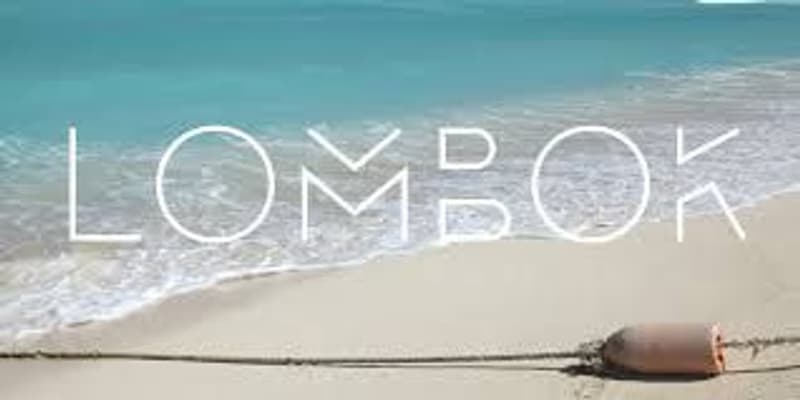
Font modern pertama adalah Lombok, karya Alexandre Pietre. Dengan asal-usul dari tipografi serif, font ini menampilkan huruf tanpa garis proyeksi atau ikal di ujungnya. Meskipun tampak samar, gaya font ini tetap tegas dan jelas terlihat.
02 Ailerons
Ailerons – Inspirasi Pesawat Terbang 1940an oleh Adilson Gonzales de Oliveira Junior
Adilson Gonzales de Oliveira Junior menciptakan Ailerons, sebuah font unik yang terinspirasi oleh model pesawat terbang pada era 1940an. Ujung setiap hurufnya miring dan sedikit melengkung dengan detail yang halus.
03 One Day
One Day – Font Ramping dengan Sentuhan Visual Menarik dari Nawras Moneer
One Day, karya Nawras Moneer, adalah font ramping dengan huruf besar yang memikat. Bentuk font bulat dan garis putus-putusnya menambahkan daya tarik visual pada judul utama.
04 Cooper Hewitt
Cooper Hewitt – Sans Serif Kontemporer dari Museum Desain Cooper Hewitt Smithsonian
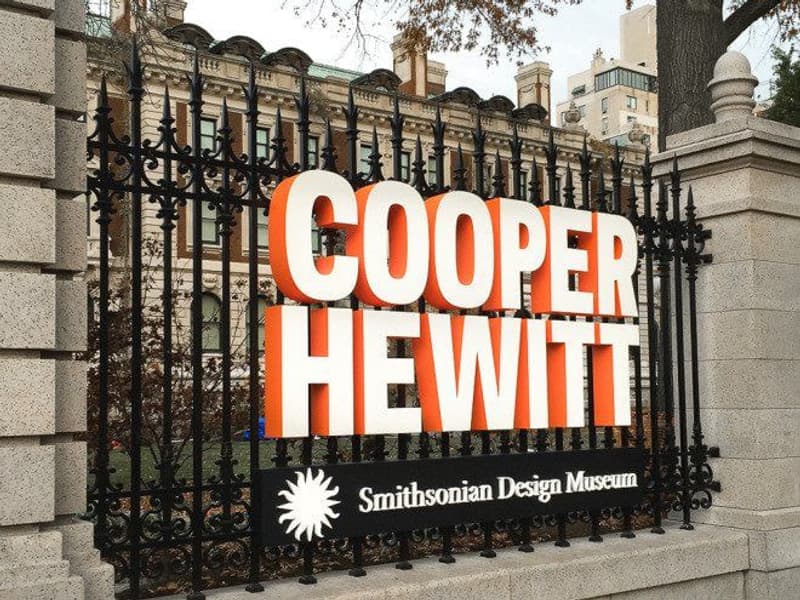
Museum Desain Cooper Hewitt Smithsonian melibatkan perancang Chester Jenkins untuk menciptakan font sans serif kontemporer sebagai bagian dari revitalisasi bangunan dan identitasnya. Font ini tersedia gratis untuk keperluan umum dan cocok digunakan dalam desain brand masa kini.
05 Aqua
Aqua – Garis Lurus Kontras dengan Bentuk Bulat dari Laura Pol
Font unik Laura Pol, Aqua, menampilkan garis lurus kontras dengan bentuk yang sangat bulat. Huruf besar didominasi oleh sudut yang kuat, sementara huruf kecil memiliki lingkaran halus yang mendominasi.
06 Kolikö
Kolikö – Sans Serif Geometris dengan Karakter Latin dan Cyrillic dari Fontfirma
Keluarga font Kolikö dari Fontfirma memiliki karakter Latin dan Cyrillic dalam gaya reguler, tipis, dan tebal. Sebagai font sans serif geometris, Kolikö memiliki struktur bersih yang cocok untuk berita utama yang tebal.
07 Polya
Polya – Modern dengan Inspirasi Jaring Poli-Poli oleh Pilar Adrien
Pilar Adrien menciptakan font Polya yang terinspirasi dari jaring poli-poli, yakni jala untuk pemodelan komputer 3D. Font ini memiliki bentuk tebal dan tampilan yang ringan, menampilkan gaya multi-fungsi.
08 Radnika
Radnika – ‘Medium’ yang Menjembatani Kesenjangan Tipografi oleh Alfredo Marco Pradil
Alfredo Marco Pradil mendeskripsikan font Radnika-nya sebagai “tipe pekerja keras.” Ini adalah jenis huruf multi-fungsi yang menjembatani kesenjangan antara tipografi abad ke-19 yang kuat dan ekspresif, dan tipografi abad ke-20 yang halus dan buram.
09 Modeka
Modeka – Ringan dan Elegan dengan Detail yang Membulat dari Gatis Vilaks
Modeka, hasil karya Gatis Vilaks, adalah font ringan dan elegan yang menggabungkan sudut dengan detail yang membulat. Set karakternya menampilkan persimpangan yang terlihat antara bagian masing-masing elemen.
10 Higher
Higher – Ideal untuk Berita Utama dengan Tampilan Memanjang dari Marisa Passos
Awalnya dirancang untuk proyek sekolah, font Higher oleh Marisa Passos kemudian ditawarkan secara gratis untuk penggunaan umum. Ideal untuk berita utama, Higher memiliki tampilan yang memanjang dengan bentuk yang rapat pada bagian atas atau bawah setiap karakter.
Unduh di Bēhance.
Baca juga: 12 Font Ramadhan Khusus Desain Bertemakan Lebaran
11 Nordik
Nordik – Eksperimental dan Terinspirasi oleh Runic Norwegia dari Yana Bereziner
Nordik adalah font modern bergaya eksperimental yang didesain oleh Yana Bereziner. Terinspirasi oleh runic Norwegia, font ini mengadopsi huruf yang digunakan sebagai bahasa Jerman sebelum diadaptasi menjadi alfabet Latin.
Unduh di Bēhance.
12 Komoda
Komoda – Font Ramping dengan Gaya Modern dari Asia Ang
Asia Ang menciptakan Komoda, sebuah font ramping yang sangat cocok untuk jenis huruf berita utama dan judul. Desainnya terlihat sangat modern dengan bingkai garis persegi panjang yang mengelilinginya.
Unduh di Bēhance.
13 Kollektif
Kollektif – Alternatif Kontras Rendah dari Brave New Fonts
Sebagai alternatif untuk tipografi berkontras rendah pada abad ke-21, Brave New Fonts merancang Kollektif. Font aesthetic ini dapat digunakan untuk tampilan dan blok teks, tersedia dalam dua gaya serta dua bobot.
14 Achi
Achi – Font Eksperimental dengan Sentuhan Art Deco dari Shibu PG
Achi, karya Shibu PG, adalah font eksperimental dengan gaya modern dan kontemporer. Garis ganda stem dan stroke menambahkan sentuhan detail Art Deco yang memukau.
Unduh di Bēhance.
15 Parley
Parley – Gaya Modern dengan Garis Diagonal Menarik dari Filipe Rolim
Filipe Rolim menciptakan Parley dengan garis diagonal yang menarik, memotong setiap huruf dan angka. Beberapa potongan menjadi bagian dari karakter, sementara yang lain menambahkan detail tambahan yang unik.
Unduh di Bēhance.
16 Aroma
Aroma – Gaya Kontemporer dengan Sentuhan Retro dan Kaligrafi dari Laura Pol
Laura Pol kembali menciptakan font, Aroma, yang tersedia dalam versi huruf tebal dan tipis. Bergaya kontemporer dengan lengkungan dan terminal siku yang sedikit retro dan kaligrafi.
Unduh di Bēhance.
17 Boxing
Boxing – Font Kuat Terinspirasi Poster Tinju Retro dari Tano Veron
Tano Veron memberikan pukulan berat dengan font Boxing yang memiliki bentuk kuat, memanjang, dan rapat. Terinspirasi oleh poster tinju retro, font ini sesuai dengan namanya yang kuat.
Unduh di Bēhance.
18 Minimalust
Minimalust – Font Bersih dan Minim dengan Sentuhan Vintage dari Pratama Yudha
Minimalust, desain Pratama Yudha, adalah font bersih dan minim yang terinspirasi dari tulisan tangan dan cetak vintage. Jenis huruf sans serif ini memiliki tepi yang halus dan sudut yang membulat.
Unduh di Bēhance.
19 Hyped
Hyped – Geometris dan Modern dengan Inspirasi Art Deco dari Med Ness
Med Ness membawa font Hyped dengan bentuk geometris dan ruang negatif. Beberapa karakter terinspirasi oleh Art Deco, sementara yang lain memiliki sentuhan postmodernis Memphis.
Unduh di Bēhance.
20 Metria
Metria – Geometris Serbaguna dengan Sentuhan Organik dari Jake Lunde
Metria adalah jenis huruf geometris serbaguna dengan sudut konsisten dan lingkaran yang tidak sempurna. Menurut desainer Jake Lunde, font ini terinspirasi dari bentuk geometris yang kaku yang diinfus dengan kurva organik untuk membuat kata-kata menjadi hidup.
Unduh di Bēhance.
21 Arenq
Arenq – Retro dan Futuristik dari Paulo R
Paulo R memberikan font gratis bernama Arenq, dengan bentuk dua garis yang memancarkan daya tarik retro dan futuristik. Font ini tampil sangat efektif dengan gradien atau pudar pada setiap karakter.
Unduh di Dafont.
22 Fontaine
Fontaine – Inspirasi Art Deco untuk Tampilan Dramatis dari Freebies PSD
Fontaine, mengambil inspirasi dari gaya Art Deco, cerita detektif, serta berita utama dan iklan vintage, terlihat sangat cocok untuk judul poster film. Font ini jelas, mudah dibaca, dan memberikan nuansa drama yang tepat.
Unduh di Freebies PSD.
23 Brassie
Brassie – Modern dan Kontemporer Serif dari Ryan Welch
Brassie, ciptaan Ryan Welch, merupakan font serif pertama dalam daftar ini. Meskipun memiliki serif kecil, ini tidak mengurangi pesonanya karena tetap menjadi font yang benar-benar modern dan kontemporer.
Unduh di Bēhance.
24 Moka
Moka – Tampilan Modern untuk Logo Kopi dari Liz Withers
Liz Withers menciptakan Moka sebagai jenis tampilan modern untuk logo kopi. Meskipun tidak dipilih oleh kliennya, Liz memutuskan untuk membagikannya secara gratis di Bēhance. Font sans serif ini memiliki ukuran besar pada garis dan outlinenya, memberikan sentuhan tulisan tangan yang unik.
Unduh di Bēhance.
25 Perfograma
Perfograma – Inspirasi dari IBM Harvard Mark 1 dari Fontfabric
Perfograma terinspirasi oleh IBM Harvard Mark 1, komputer elektro-mekanis yang membaca instruksi dari pita kertas 24 saluran punched paper tape. Meskipun konsepnya berasal dari tahun 1937, font ini tetap dianggap modern.
Unduh di Bēhance.
26 Ministry
Ministry – Elegan dan Memanjang dari Victor Tognollo
Ministry, hasil karya Victor Tongollo, adalah jenis huruf sans serif yang elegan dengan bentuk memanjang, kurva halus, dan batang serta ekor yang menarik, dilengkapi dengan elemen khas lainnya.
27 Unik2
Unik2 – Kontemporer dengan Sentuhan Retro dan Futuristik dari Fonts of Chaos
Unik2 dari Fonts of Chaos menampilkan tampilan kontemporer sambil masih memancarkan nuansa retro dan futuristik. Meskipun tanpa bentuk lingkaran, sudut dan terminalnya dibulatkan untuk memberikan kesan yang halus secara keseluruhan.
28 Nagasaki
Nagasaki – Terinspirasi oleh Poster Klasik dari Sasha Lacob
Font Nagasaki karya Sasha Lacob terinspirasi oleh poster klasik Wim Crouwel tahun 1953 berjudul “Hiroshima.” Dengan ketebalan dan ketepatan yang mencolok, font ini menciptakan dampak visual yang besar.
Unduh di Bēhance.
29 Hyperbola
Hyperbola – Geometri Matematis dalam Tipografi Modern dari Tarin Yuangtrakul
Dengan nama yang sesuai, Hyperbola terinspirasi dari kurva matematis. Tarin Yuangtrakul menggabungkan ciri geometri dan bayangan cermin hiperbola ke dalam tipografi modern ini.
Unduh di Bēhance.
30 Reckoner
Reckoner – Sentuhan Modern pada Tipografi Industri dari Alex Dale
Alex Dale mengambil inspirasi dari tipografi industri populer sans serif untuk menciptakan Reckoner. Meskipun tampil modern, font ini tetap mempertahankan dasar-dasar tradisional yang kuat.
Unduh di Bēhance.
Baca juga: 10 Font Terbaik Untuk Desain Kaos
31 Stoked
Stoked – Sentuhan Cinta dalam Desain Serif oleh Marie-Michelle Dupuis
Marie-Michelle Dupuis merancang Stoked, sebuah jenis huruf serif yang terlahir dari kasih sayang. Sang desainer berkata, “Font ini diselamatkan dengan cinta setelah penolakan lima logo huruf kustom. Bagaimana bisa font ini ditinggalkan begitu kejam? Lalu saya berikan font ini ke 21 teman lainnya.”
Unduh di Bēhance.
32 QG
QG – Ketidakterlihatan dengan Gaya Abstrak oleh Anthony James
Font QG karya Anthony James menghadirkan kurva sederhana dan garis abstrak yang muncul dan hilang seperti secangkir kopi atau noda gelas anggur. “Sisi sudut menambahkan berat dan menjaga agar estetika tidak terlalu kaku,” kata Anthony.
Unduh di Bēhance.
33 Qontra
Qontra – Sans Serif dengan Kontras Rendah oleh Tomaz Hrastar
Tomaz Hrastar menciptakan Qontra sebagai huruf sans serif rapat dengan kontras rendah. Garis dan lekuk yang halus sangat sesuai untuk berita utama dan teks tubuh.
Unduh di Bēhance.
34 Disclaimer
Disclaimer – Font Layar dengan X-Height Tinggi oleh Fontfabric
Disclaimer dari Font Fabric adalah font layar berbasis modul dengan bentuk memanjang dan tertutup serta x-height yang sangat tinggi.
Unduh di Bēhance.
35 Orkney
Orkney – Geometris untuk Proyek Cetak dan Digital oleh Samuel Oakes dan Alfredo Marco Pradil
Orkney, hasil karya Samuel Oakes, adalah font geometris yang dikonseptualisasikan untuk keunikan dan fungsionalitas. Cocok untuk beragam proyek cetak dan digital.
Unduh di Bēhance.
36 Prime
Prime – Sederhana dengan Nuansa ‘Teknologi’ oleh Max Pirsky
Prime oleh Max Pirsky adalah tipografi sederhana dengan nuansa ‘teknologi’ dan bentuk geometris yang ketat. Cocok untuk berita utama dan teks tubuh dengan detail yang cukup halus untuk tampil beda.
Unduh di Font Fabric.
37 Matey
Matey – Sentuhan Retro dengan Daya Tarik Modern oleh Andreas Leonidou
Matey karya Andreas Leonidou mungkin sedikit retro, tetapi masih memiliki tampilan modern dan daya tarik kontemporer. Kurva geometris dan bentuk rapatnya paling baik dibaca pada ukuran besar, menjadikannya pilihan yang tepat untuk berita utama dan judul.
Unduh di Bēhance.
38 Decurion
Decurion – Serif Lempeng yang Khas oleh Mehmet Reha Tugcu
Decurion adalah serif lempeng dengan bentuk yang tebal dan seperti blok. Mehmet Reha Tugcu merancang Decurion dalam banyak versi, termasuk inline dan outline, dan Anda bebas mengunduhnya.
Unduh di Bēhance.
39 Blanka
Blanka – Modern, Minimalis, dan Abstrak oleh Emmeran Richard
Emmeran Richard menciptakan font Blanka yang modern, minimalis, dan abstrak dengan elemen yang nampaknya dipotong pendek dan hilang.
Unduh di The Hungry Jpeg.
40 Maddac
Maddac – Kreativitas dalam Kolaborasi oleh Ishak Taracks dan Maddie May Kroll
Maddac, dinamai sesuai desainernya Ishak dan Maddie, merupakan kombinasi dari kreativitas mereka. Misi mereka adalah menciptakan jenis huruf yang bersih dan mudah dibaca, dan misi tersebut sukses dengan mengikuti dua aturan yang telah ditentukan sebelumnya.
Unduh di Bēhance.
Baca juga: 16 Font Aesthetic Rekomendasi Para Desainer
41 Leoscar
Leoscar – Elegan dan Ringan dengan Sentuhan Modern dari Faridul Haque
Faridul Haque menciptakan Leoscar, sebuah tipografi modern dengan variasi serif dan sans serif. Font ini elegan dan ringan, dengan detail desain yang halus.
Unduh di Bēhance.
42 Amsterdam Superstar
Amsterdam Superstar – Geometris dan Futuristik dari Fonts of Chaos
Amsterdam Superstar adalah font yang memiliki semua garis dan sudut membentuk tampilan yang sangat geometris dan hampir futuristik. Setiap karakternya memiliki ruang persegi, memberikan tinggi dan lebar yang sama.
43 Rodus
Rodus – Bentuk Bulat dan Persegi dengan Variasi Gaya dari Fontark
Rodus menampilkan sudut bulat dan bentuk persegi dalam empat variasi gaya, yaitu reguler, bulat, persegi, dan terpotong, serta empat ketebalan yang berbeda.
Unduh di Free Fonts 4 All.
44 Distrito
Distrito – Modular Geometris dengan Inspirasi Sejarah dari Carlo Pico
Carlo Pico merancang Distrito, sebuah font modular geometris yang terinspirasi oleh pusat sejarah Bogotá, Kolombia. Kurva font ini memiliki sudut yang menarik, memberikan sentuhan drama dan dampak.
Unduh di Da Font.
45 Etna
Etna – Tebal, Modern, dan Fungsional dari Krisijanis Mezulis
Etna dari Krisijanis Mezulis adalah font besar yang tebal dan modern. Bersih, jelas, dan fungsional, cocok untuk berbagai keperluan desain.
Unduh di Bēhance.
46 Intro
Intro – Struktur Geometris Kuat dari Font Fabric
Intro oleh Font Fabric memiliki struktur geometris yang kuat dengan karakter berdasarkan bentuk unsur seperti segitiga, lingkaran, dan kuadrat. Font ini menonjolkan sudut tajam dan bentuk tebalnya.
Unduh di Font Fabric.
47 Manifesto
Manifesto – Terinspirasi oleh Gerakan Rasionalis Italia dari Tomaz Leskovec
Font Manifesto karya Tomaz Leskovec terinspirasi oleh gerakan rasionalis Italia. Desainer bermain dengan posisi elemen karakteristik huruf, menciptakan tampilan yang unik.
Unduh di Bēhance.
48 Noir
Noir – Sederhana dan Langsung ke Inti oleh Matthias Guggisberg
Noir adalah font sederhana dan langsung ke inti, sesuai dengan namanya. Didesain oleh Matthias Guggisberg, font ini memiliki struktur geometris dan bentuk sans serif yang fungsional dan mudah dibaca.
Unduh di Bēhance.
49 Glober
Glober – Geometris Klasik dengan Sentuhan Fantastis dari Font Fabric
Glober dari Font Fabric terinspirasi oleh tipografi klasik yang fantastis. Dengan bentuk geometris yang ringan dan elegan, font ini memiliki gaya unik, terutama pada huruf kecil ‘g’ yang desainnya sangat ideal untuk mendesain kaos merchandise grup band Anda.
Unduh di Font Fabric.
50 Canter
Canter – Semua Kapital dan Rapat oleh Font Fabric
Dirancang oleh Christopher J. Lee, Canter adalah jenis huruf semua-kapital dan rapat. Font ini cocok sebagai tampilan untuk judul, berita utama, dan poster.
Baca juga: 25 Font Logo yang Harus Diketahui Setiap Desainer
Pertimbangkanlah font modern mana yang menjadi pilihan Anda!
Jangan lupa untuk mempertimbangkan apakah konten tersebut akan dipublikasikan secara digital, seperti dalam format PDF, atau dicetak, karena hal ini akan mempengaruhi ukuran dan gaya font yang digunakan.